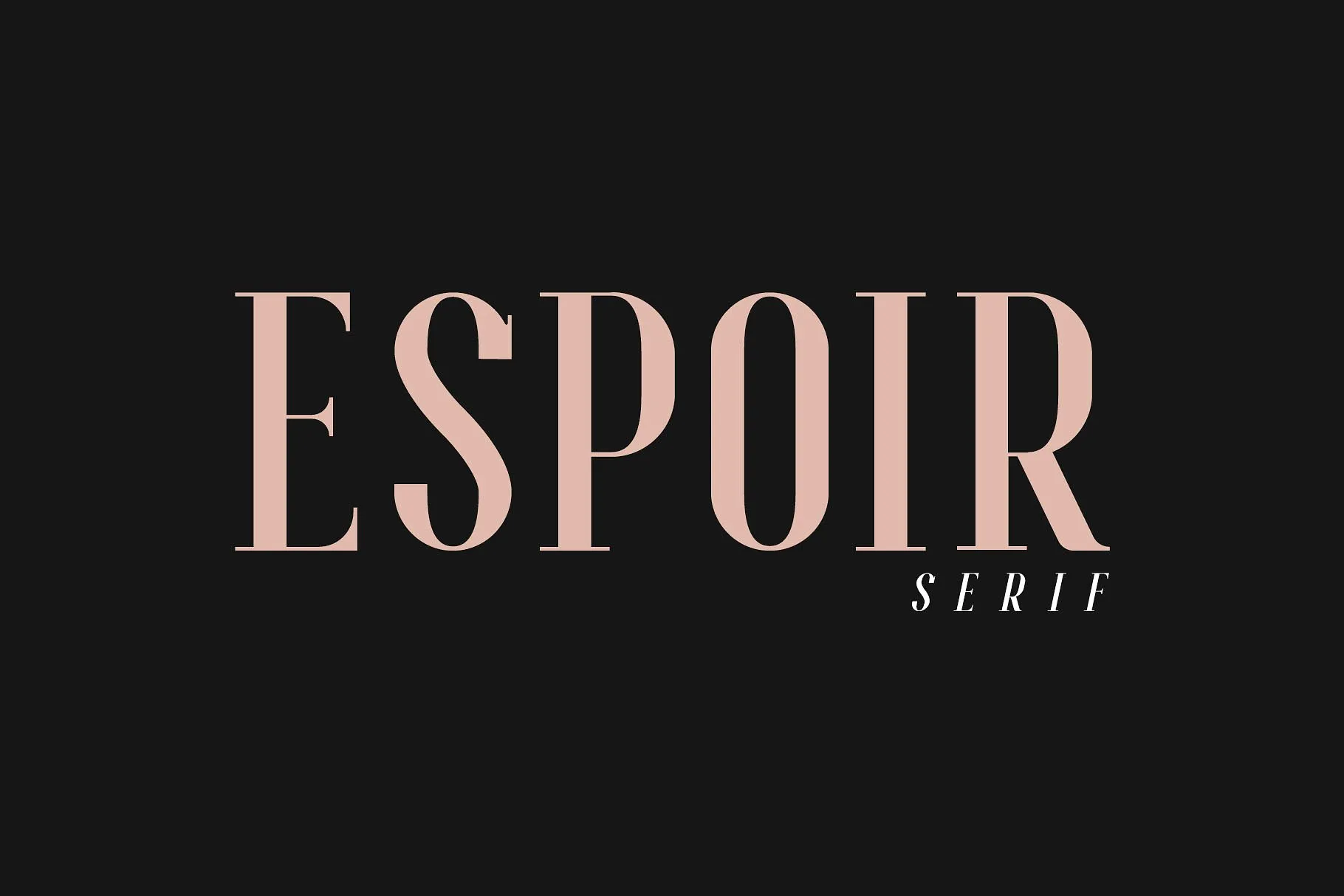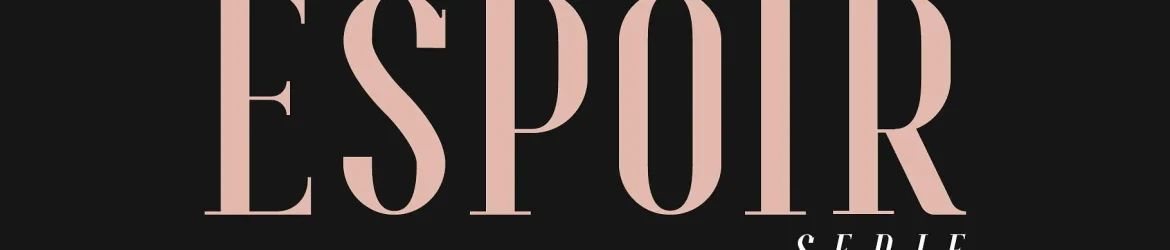
A Espoir Serif é uma família de fontes serif que traz um contraste alto, mas com um design que remete aos tempos do Transitional Serif. Esta fonte moderna foi especialmente projetada para acomodar diversos tipos de projetos gráficos. Um dos seus principais recursos diferenciais são os traços sem grande contrasto, as formas quadradas e estilizadas de caracteres redondos, e seu ar arrumado, que transmite uma sensação profissional. Este é um recurso da Espoir Serif Font Family que vale a pena destacar para designers em busca de uma fonte com um contraste alto mas sem perder sua elegância tradicional dos traços serifados.